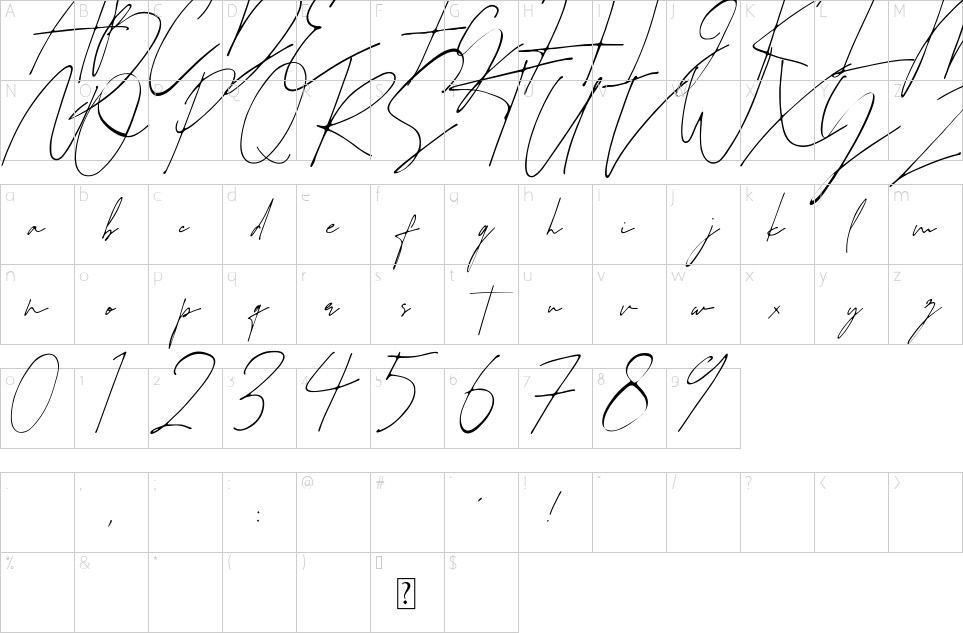
A fonte Juliette é uma escolha perfeita para designers gráficos que procuram uma fonte elegante e versátil. Desenvolvida por Ferry Ardana Putra, a Juliette oferece uma ótima combinação de simplicidade e elegância, tornando-a ideal para aplicativos variados como banners, logotipos e materiais de marketing. Com seu design limpo e agradável aos olhos, a Juliette é uma fonte que ressaltará sua identidade visual e ajudará a transmitir uma mensagem forte. Este é um recurso gratuito de fonte que já foi baixada 4.301 vezes, o que mostra sua popularidade e valor. Quer adicionar um toque de elegância e sofisticação a seu trabalho? Experimente a Juliette e descubra por si mesmo seu impacto. Esta fonte é uma excelente escolha para designers gráficos em busca de uma opção de fonte versátil e moderna.